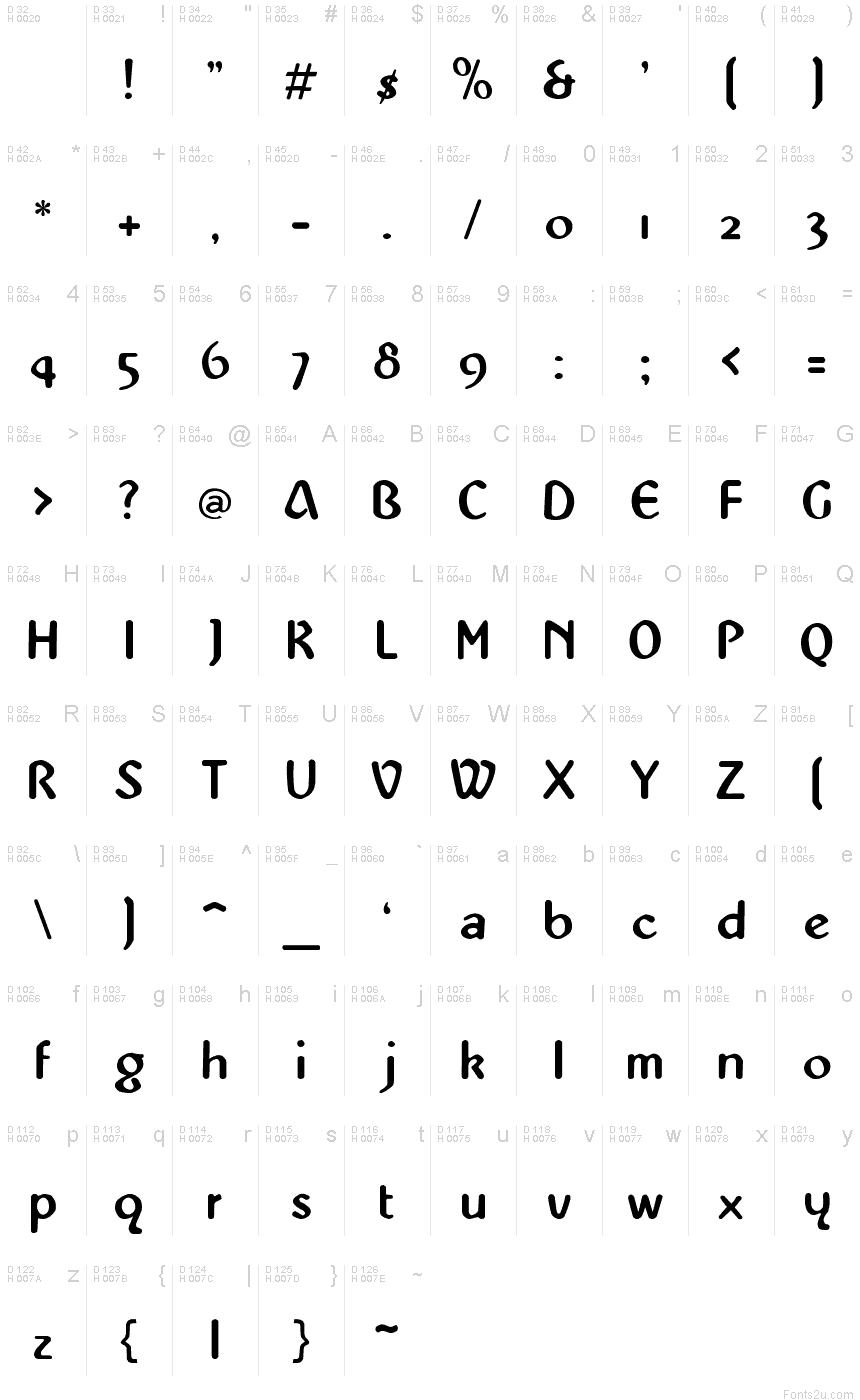
Abbey Medium to urzekający font typu display, który emanuje zachwycającym stylem retro. Jego charakterystyczne kształty liter, z zabawnymi krzywiznami i zaokrąglonymi krawędziami, przywołują nostalgiczną atmosferę rodem ze starych szyldów i designu połowy XX wieku. Dzięki swojej wyrazistej formie, font ten jest doskonałym wyborem do tworzenia śmiałych nagłówków, plakatów czy materiałów brandingowych, które mają przyciągać wzrok. Wszechstronność Abbey Medium pozwala na płynne łączenie estetyki współczesnej z inspiracjami vintage, co czyni go cennym narzędziem dla projektantów pragnących nadać swoim pracom ponadczasowego uroku.
Solidny, a jednocześnie pełen fantazji charakter tego kroju pisma świetnie sprawdza się w różnorodnych zastosowaniach – od brandingu i opakowań w klimacie retro po przykuwające uwagę projekty edytorskie. Wyjątkowa osobowość i silne oddziaływanie wizualne sprawiają, że Abbey Medium jest nieocenionym narzędziem dla twórców, którzy chcą kreować odważne, zapadające w pamięć projekty, które zachwycą odbiorców.